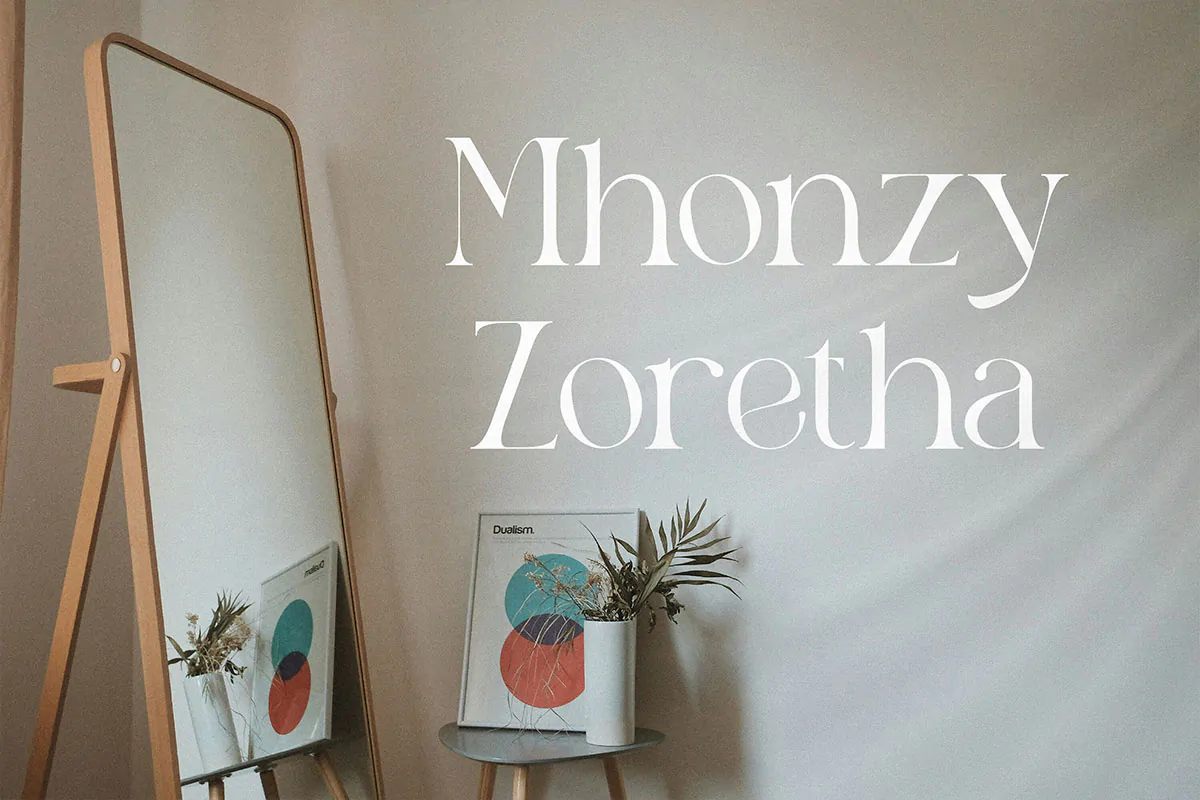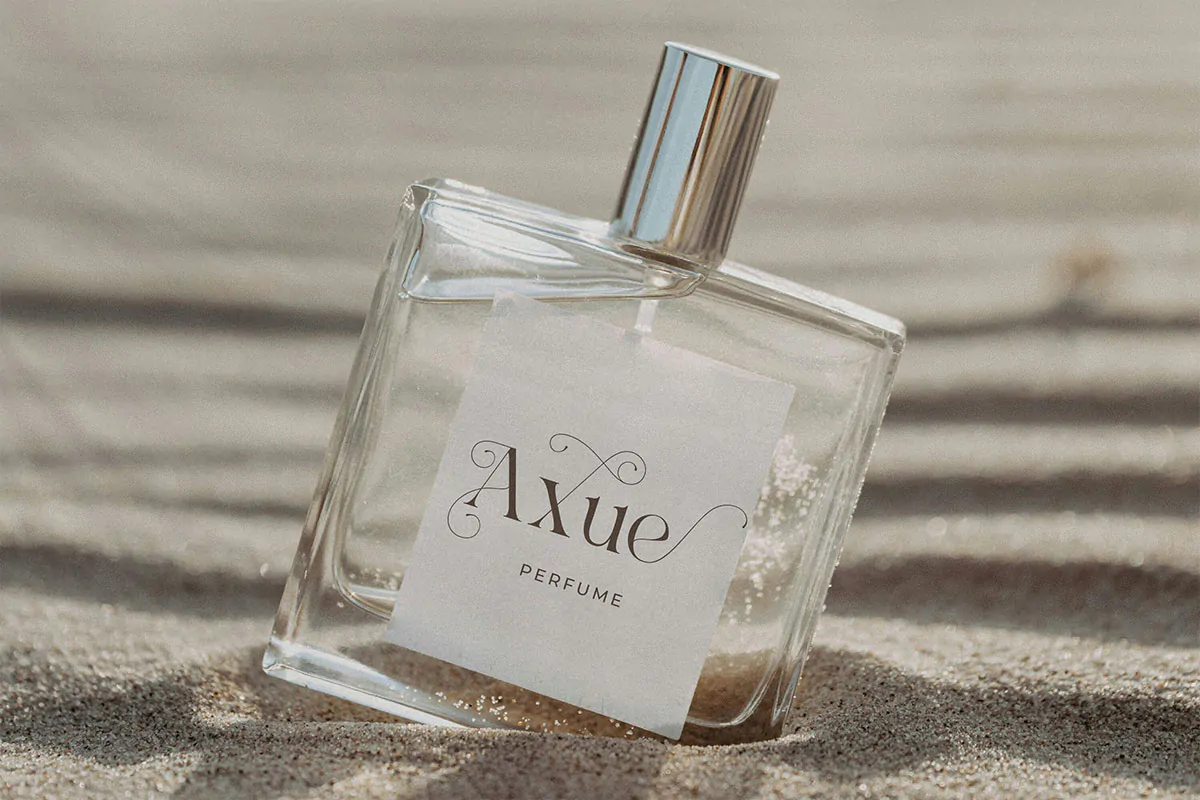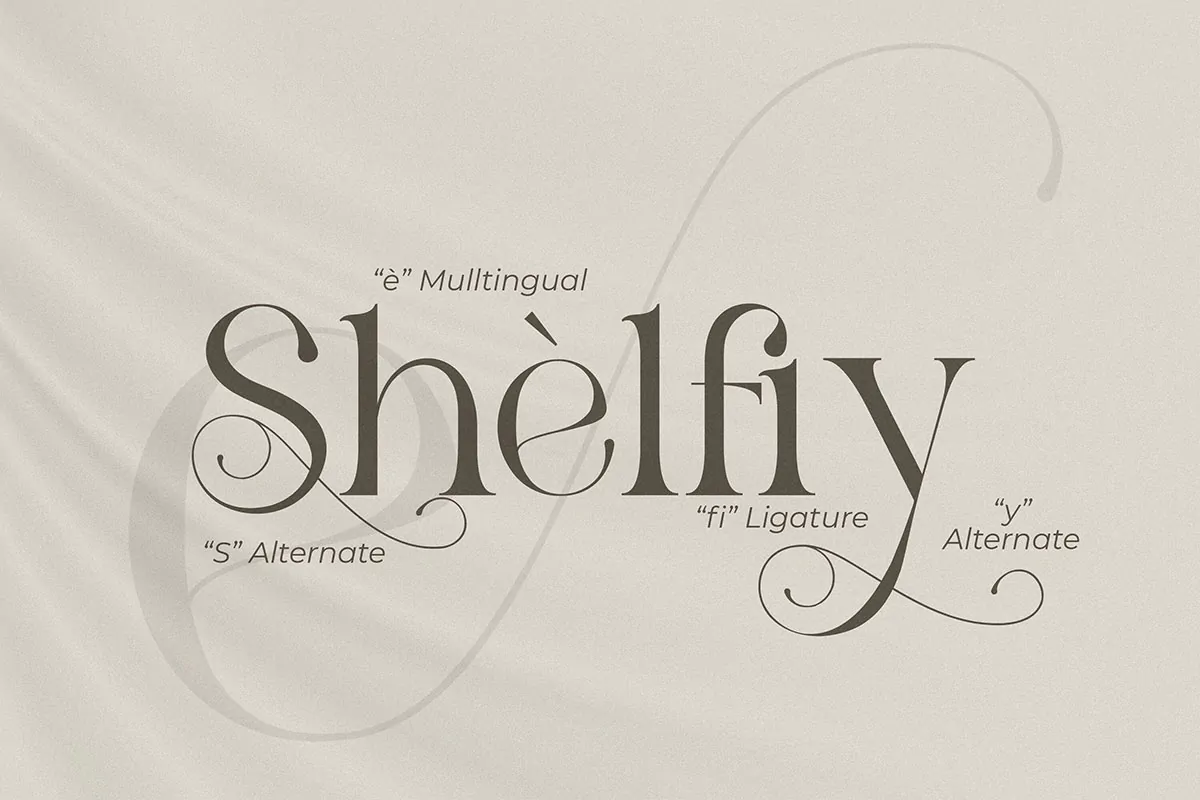
فونت مدرن و زیبای Lonety
فونت مدرن و زیبای انگلیسی
فونت مدرن و زیبای Lonety یک قلم سریف انگلیسی است که میتوانید در طراحی انواع کارت تبریک، کارت عروسی، بسته بندی محصولات، آرایشی و بهداشتی و … از آن استفاده کنید. از حروف حالت دار این فونت میتوانید در نرم افزار فتوشاپ استفاده کنید.